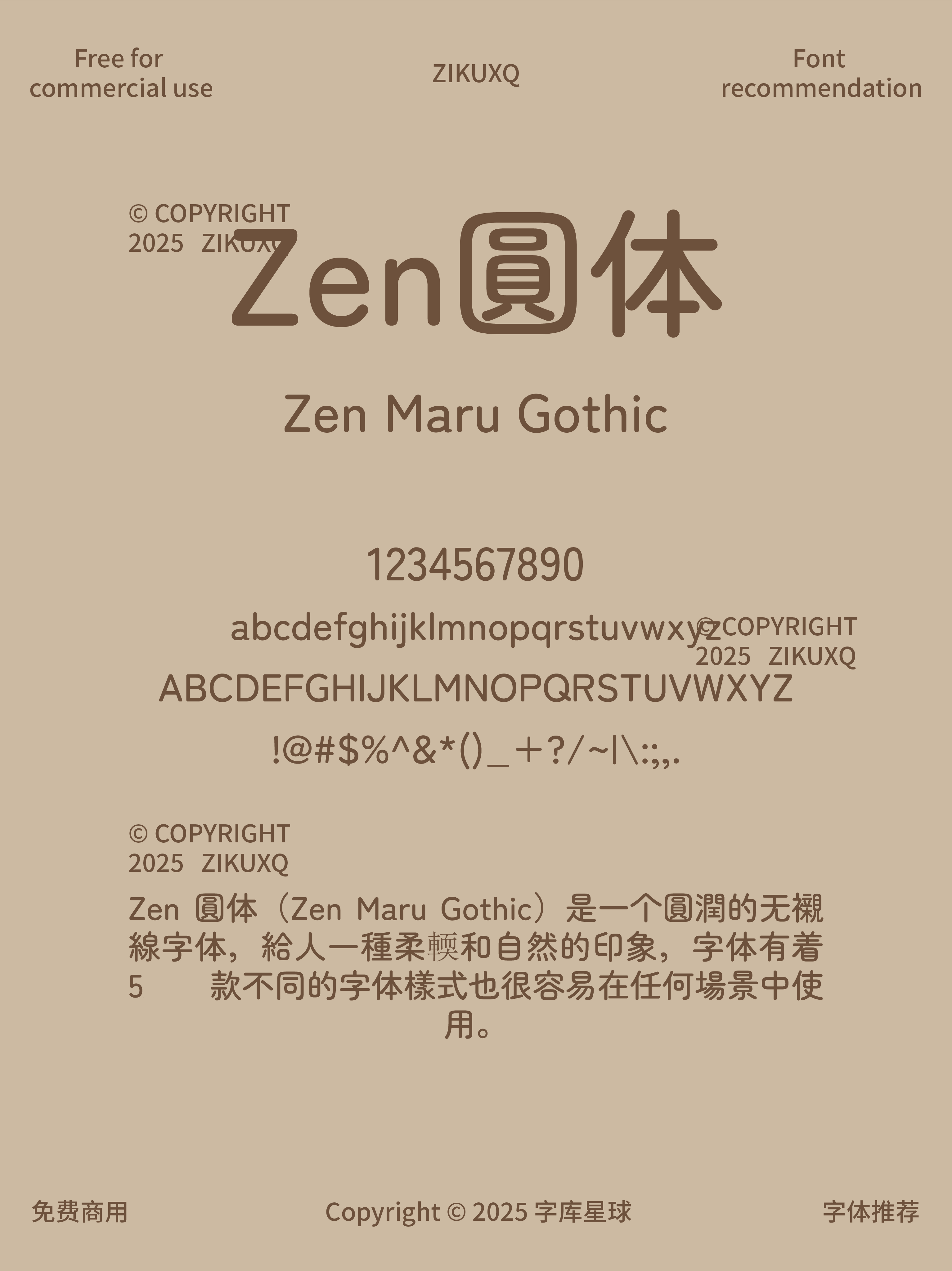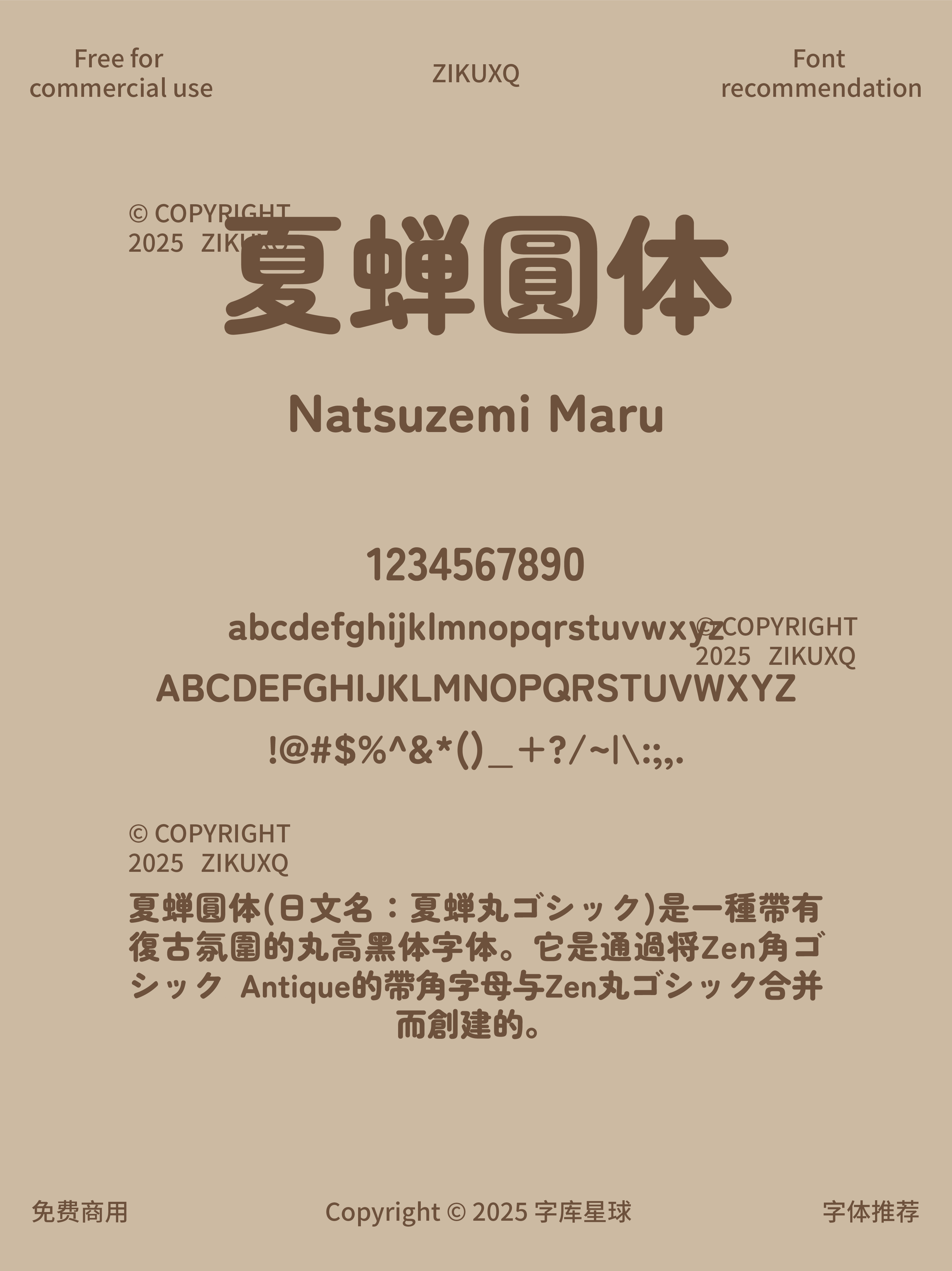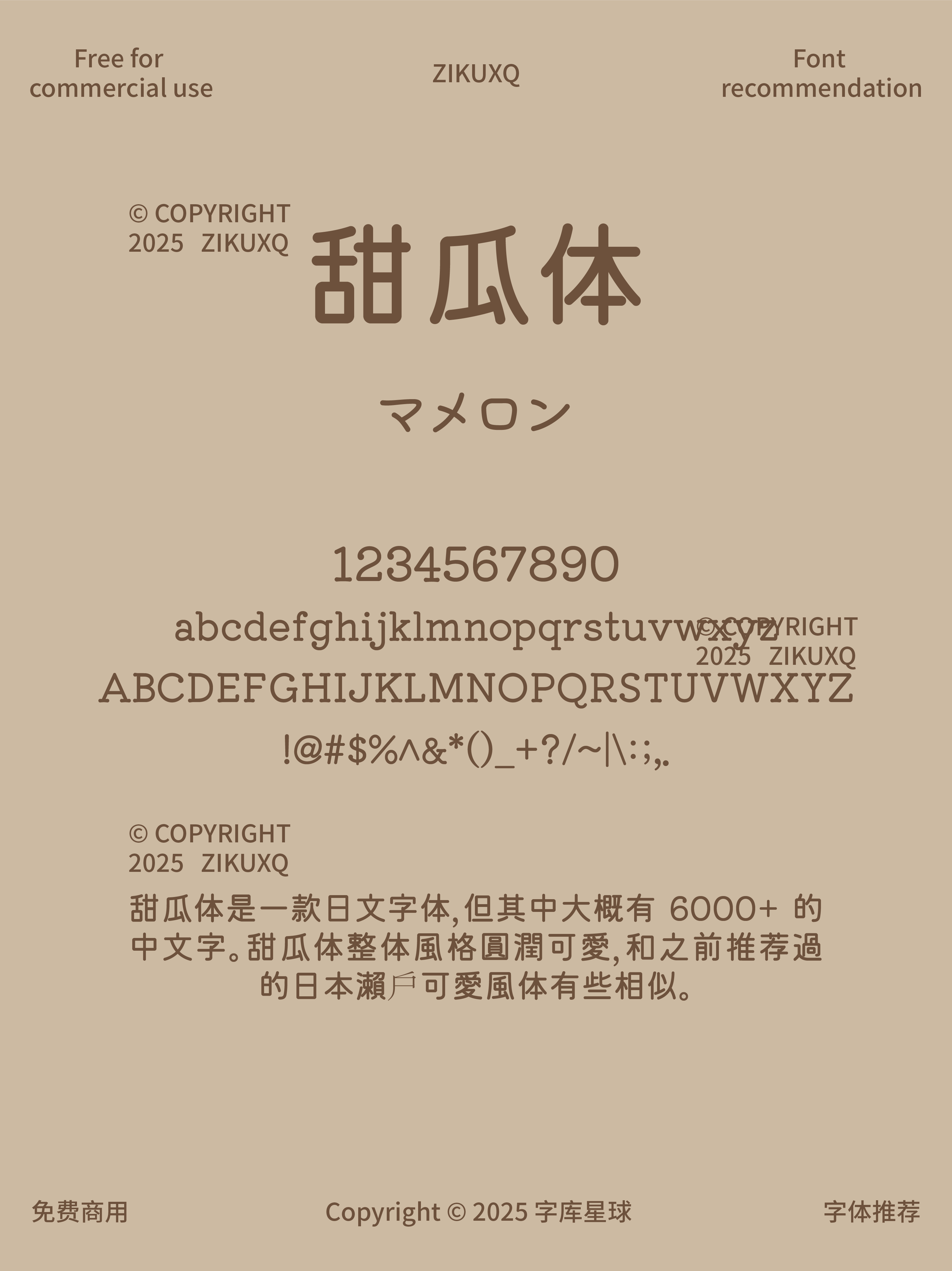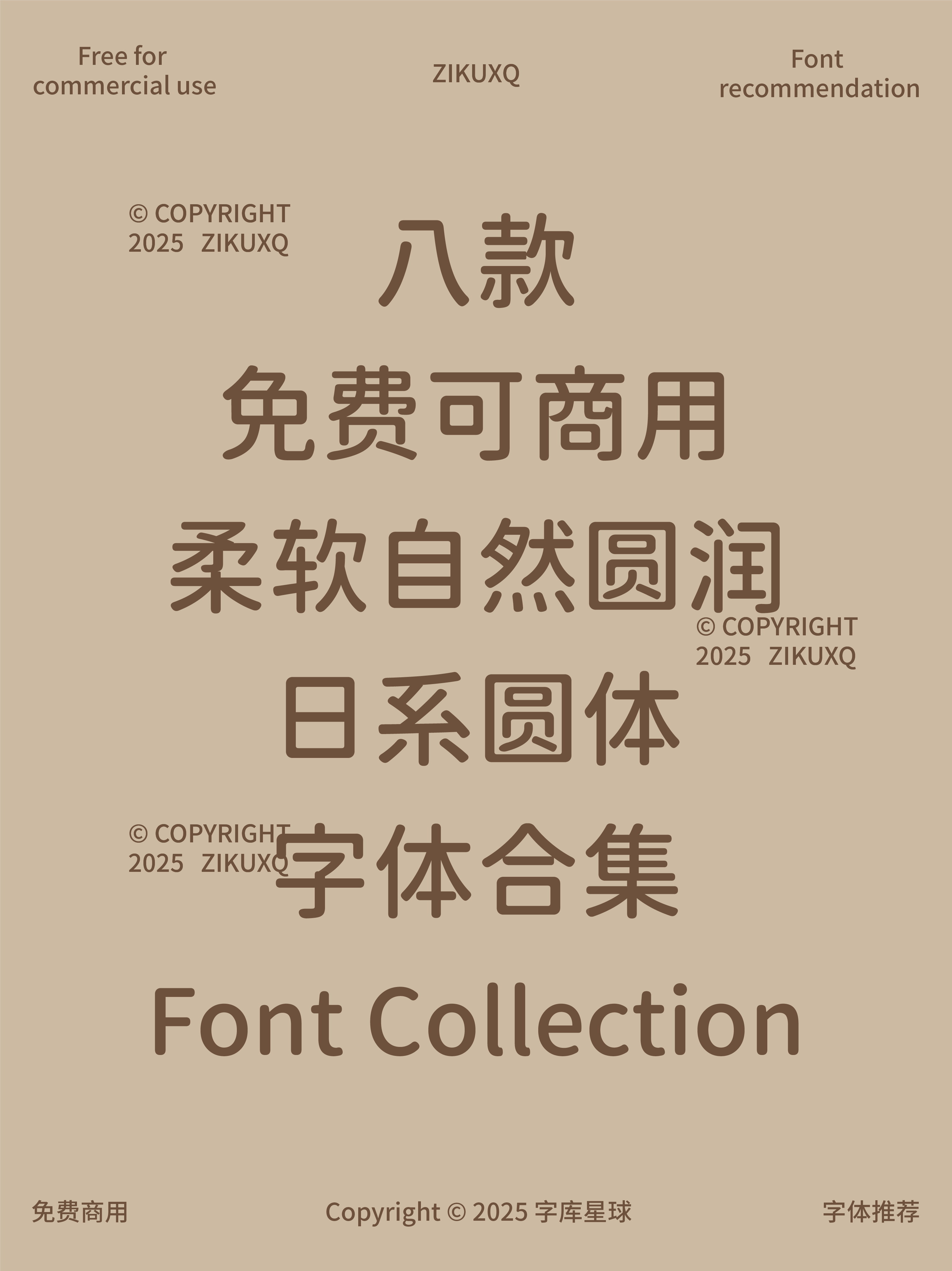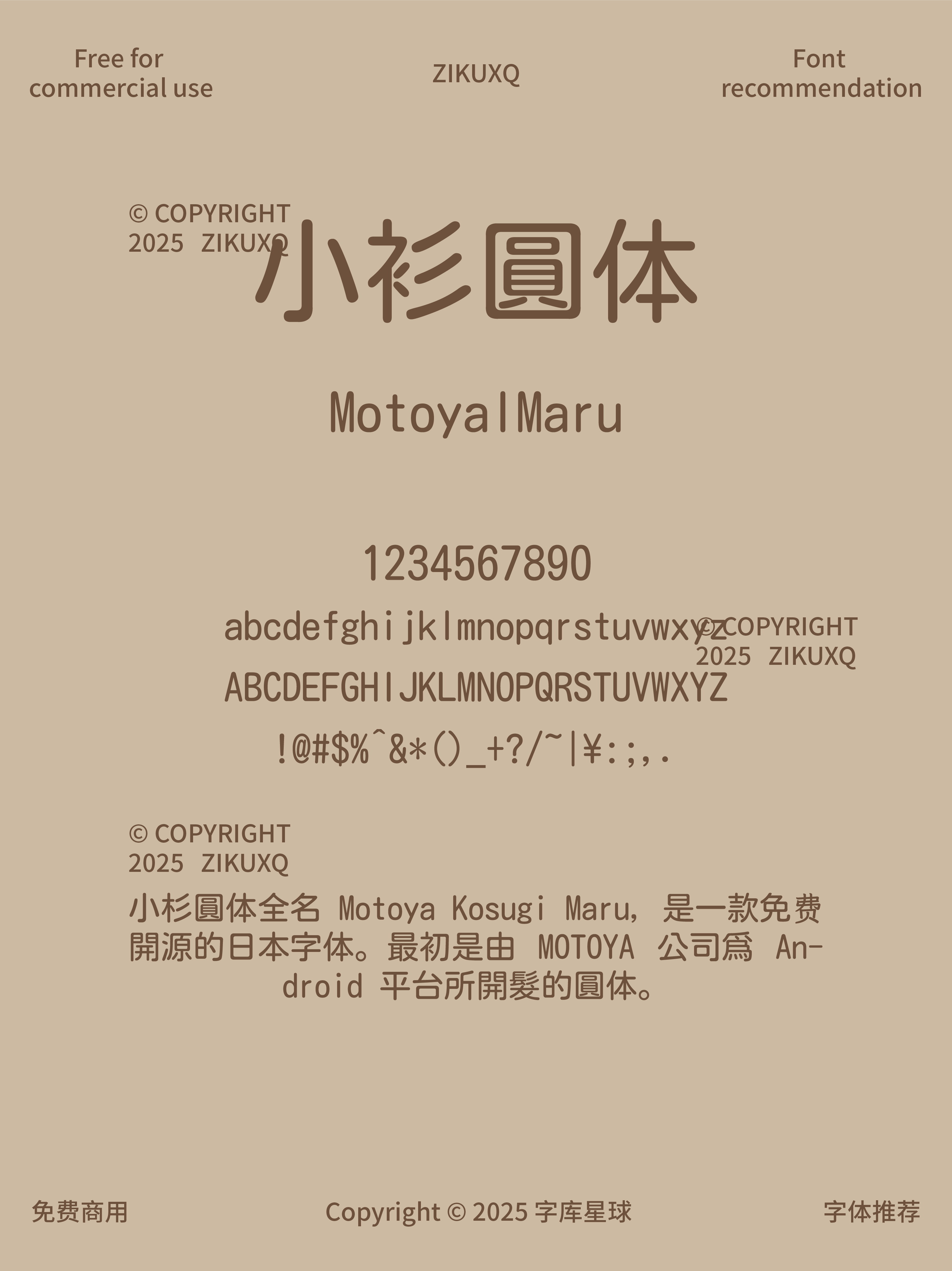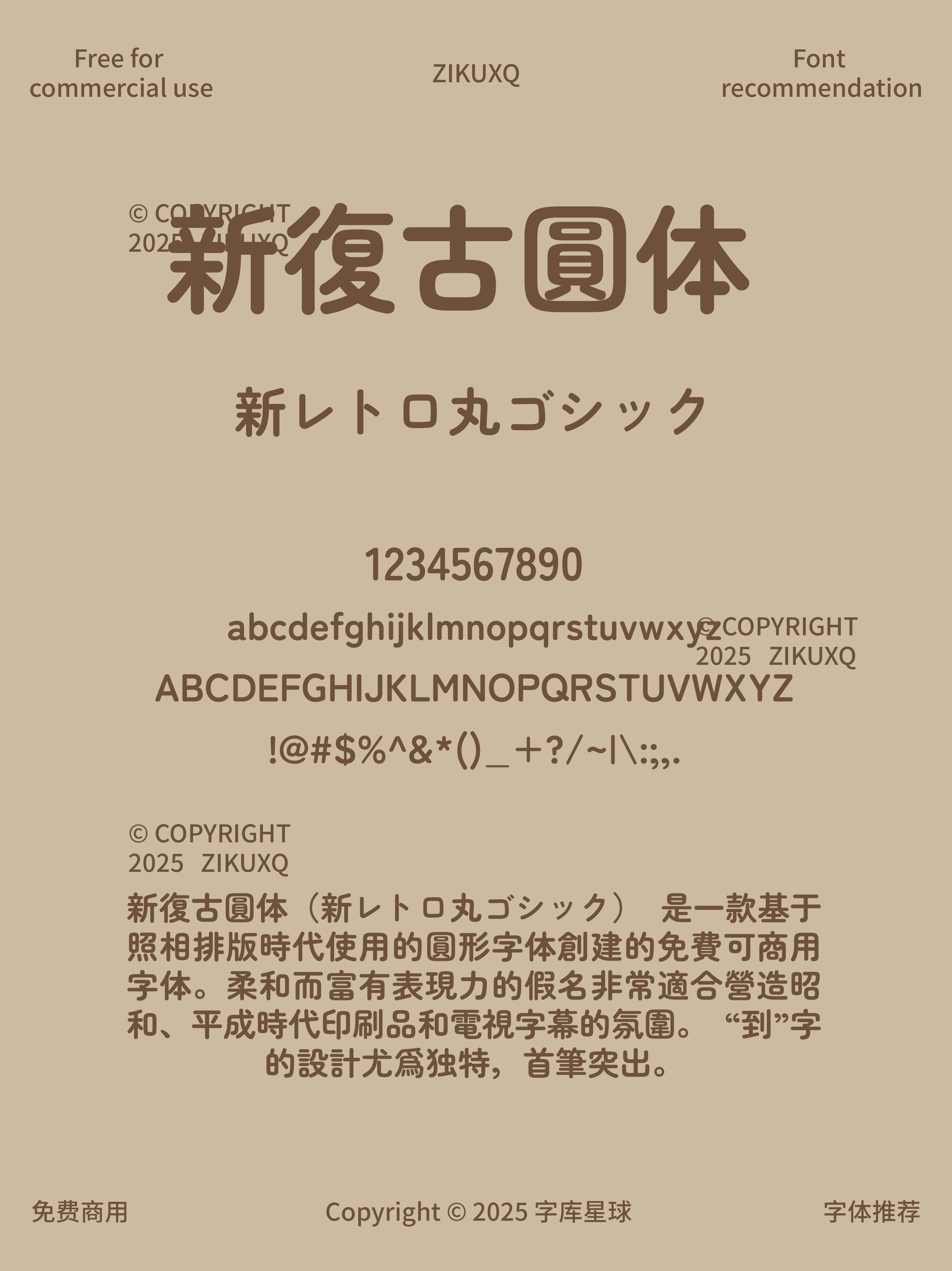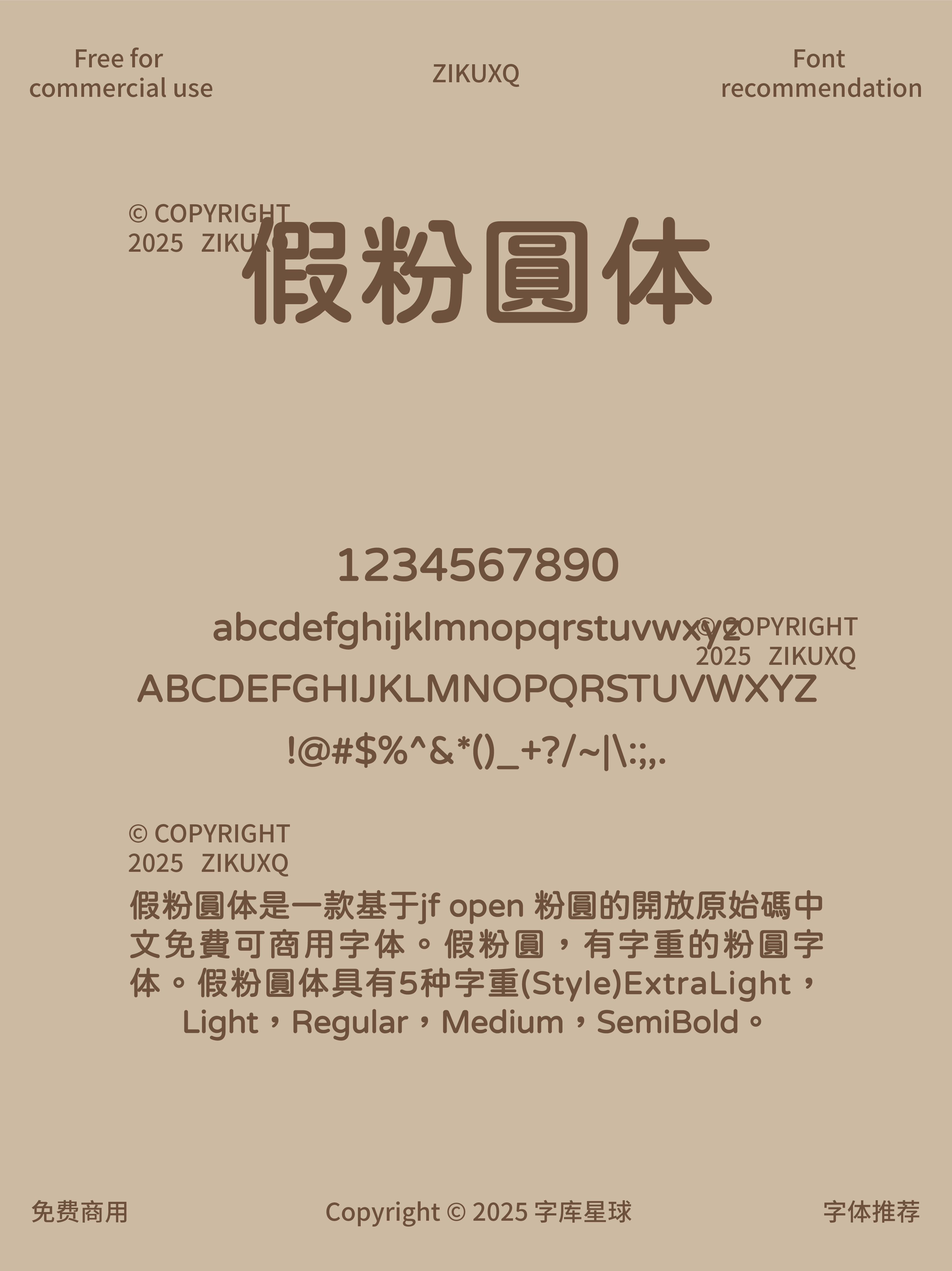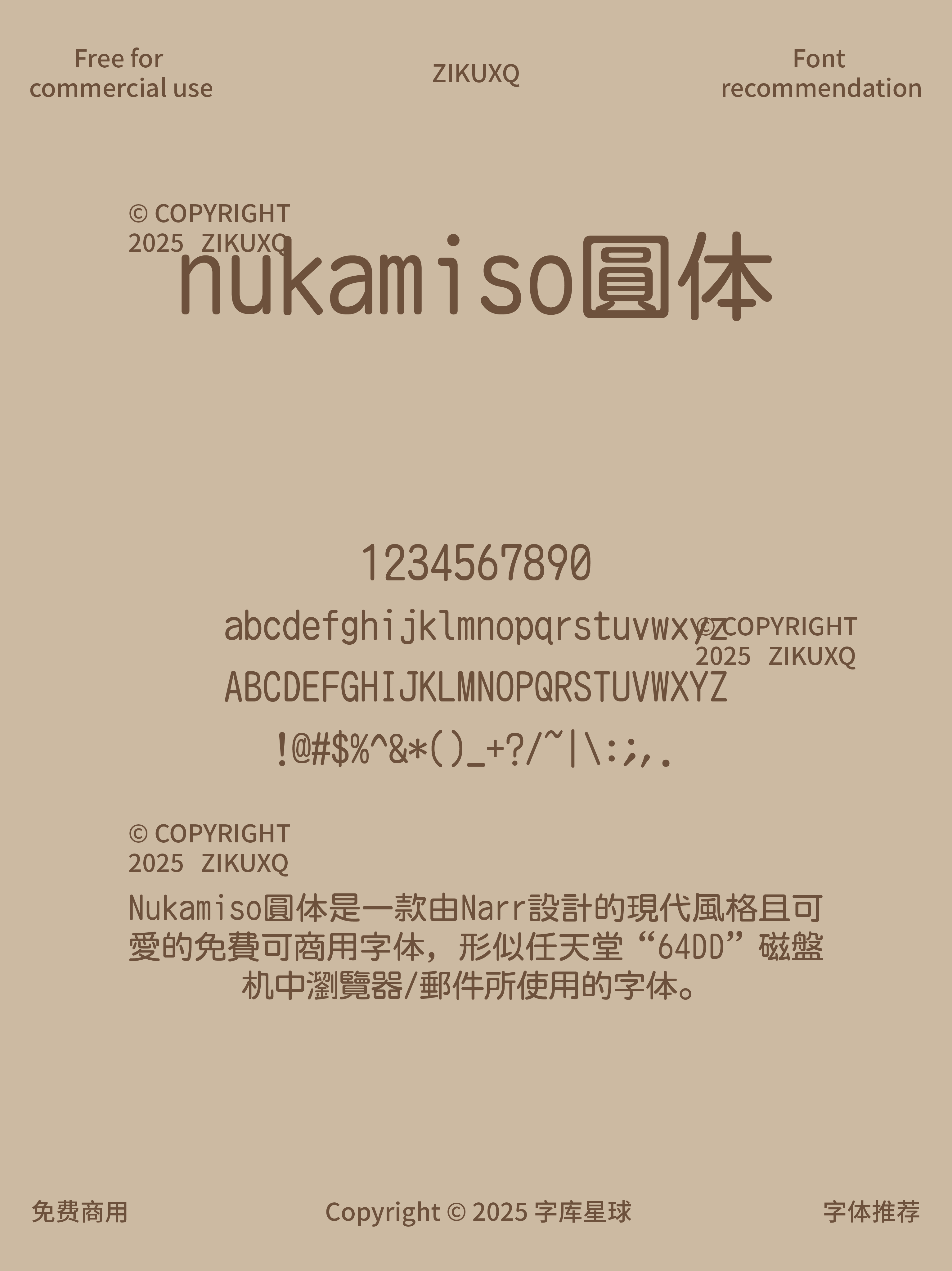
八款免费可商用柔软自然圆润的日系圆体
给大家分享超宝藏的字体啦,这次是超有氛围感的日系圆体,重点是全部免费可商用,设计 er 狂喜!快码住慢慢用~
字形方正圆润,笔画横平竖直、粗细相等,极为规整。而且还进行了圆角设计,使整体气质亲和力满分。这款免费商用的英文字体,可使用性超高,在涉及英文排版的设计中,是不错的选择。